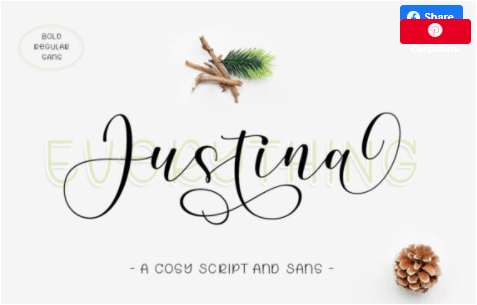
[creativefabrica] Justina Duo Font (2022)
Justina — это красивый дуэт шрифта (без засечек и шрифта), специально созданный для тех, кому в дизайне нужна нотка элегантности и современности. Этот красивый шрифт идеально подходит для логотипов, упаковки продуктов, свадебных приглашений, брендинга, заголовков, вывесок, этикеток, подписей, обложек книг, плакатов, цитат и многого другого.